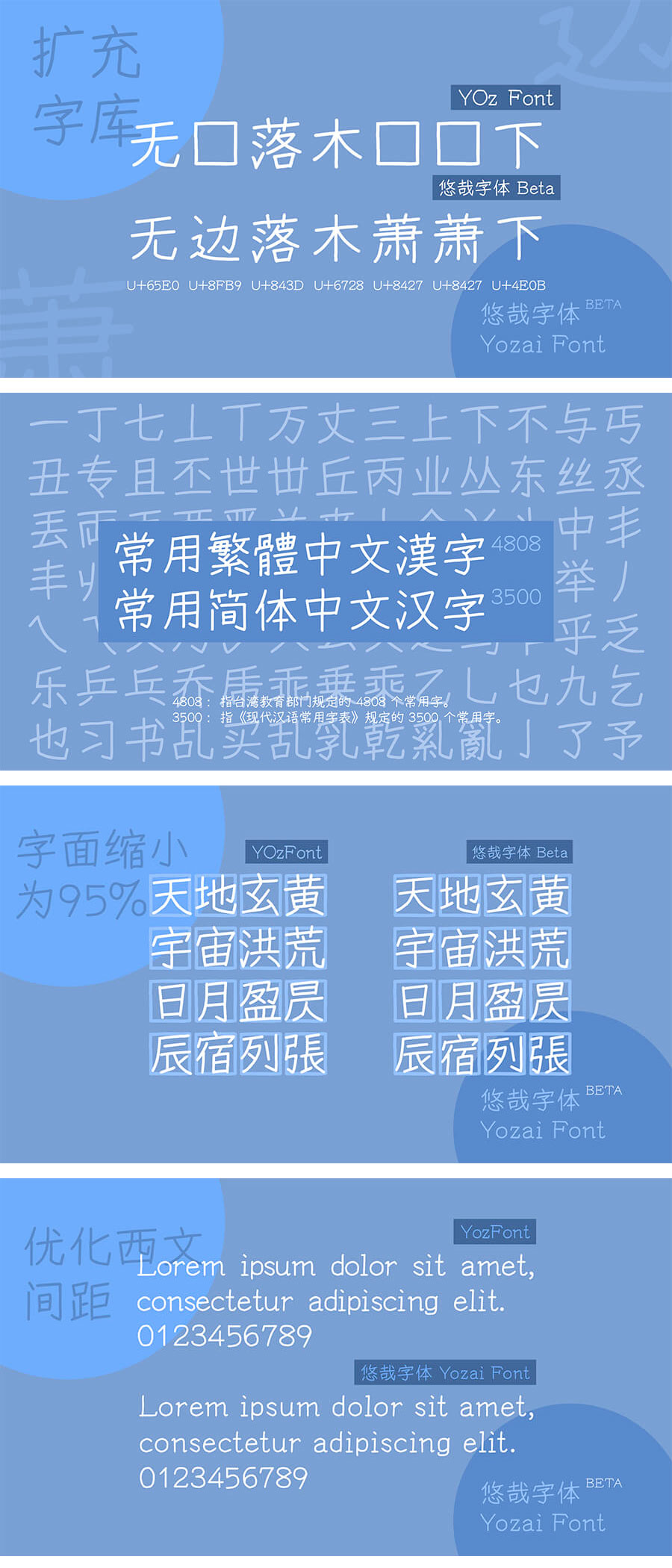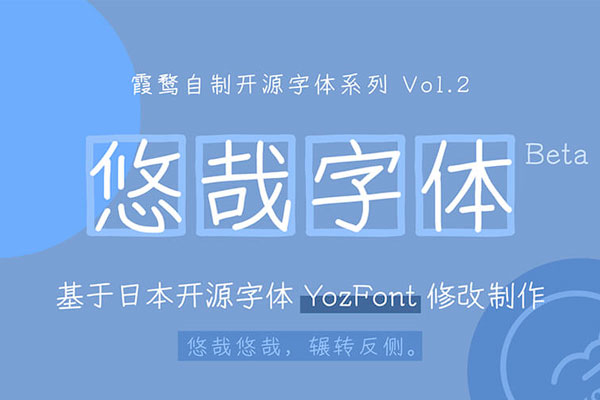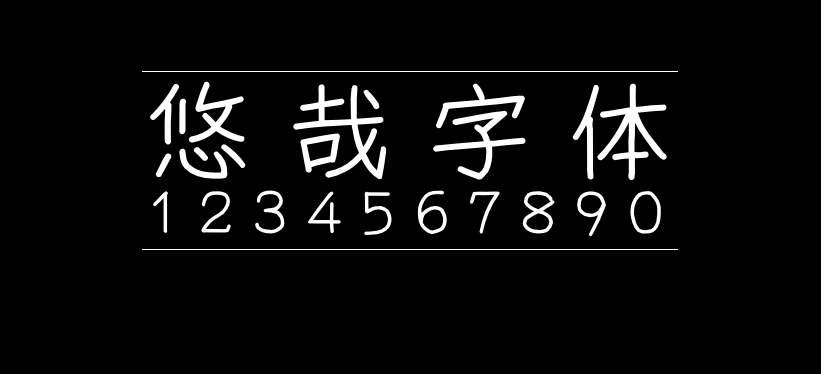
悠哉字体
悠哉字体(Yozai Font)是一款基于免费开源的Y.OzFont(日本)的手写风格的字体,作者是中国大陆的落霞孤鹜。目前已补全原字体中有对应繁体字的简体字,并补全了4808常用繁体中文汉字,以及3500常用简体中文汉字。
4808 常用繁体中文汉字是指台湾教育部门规定的 4808 个常用汉字。3500常用简体中文汉字是指《现代汉语常用字表》规定的 3500 个常用汉字。
悠哉字体在原Y.OzFont的基础上,字面缩小至原来的 95%,并优化西文和标点符号的显示。
需要注意的是:本字体目前为测试版,部分汉字还是日本写法。计划补全 GB2312 范围内的所有汉字,并更正GB2312 内汉字的写法为中国内地的字形。字体发布者并不是专业的设计师,并未考虑设计美感,所以有些字可能会看起来有点奇怪,补进去的字与原版可能略有违和感。
2021-07-19悠哉字体更新到v0.85版本,扩展了字重,现在已经拥有4个字重了。